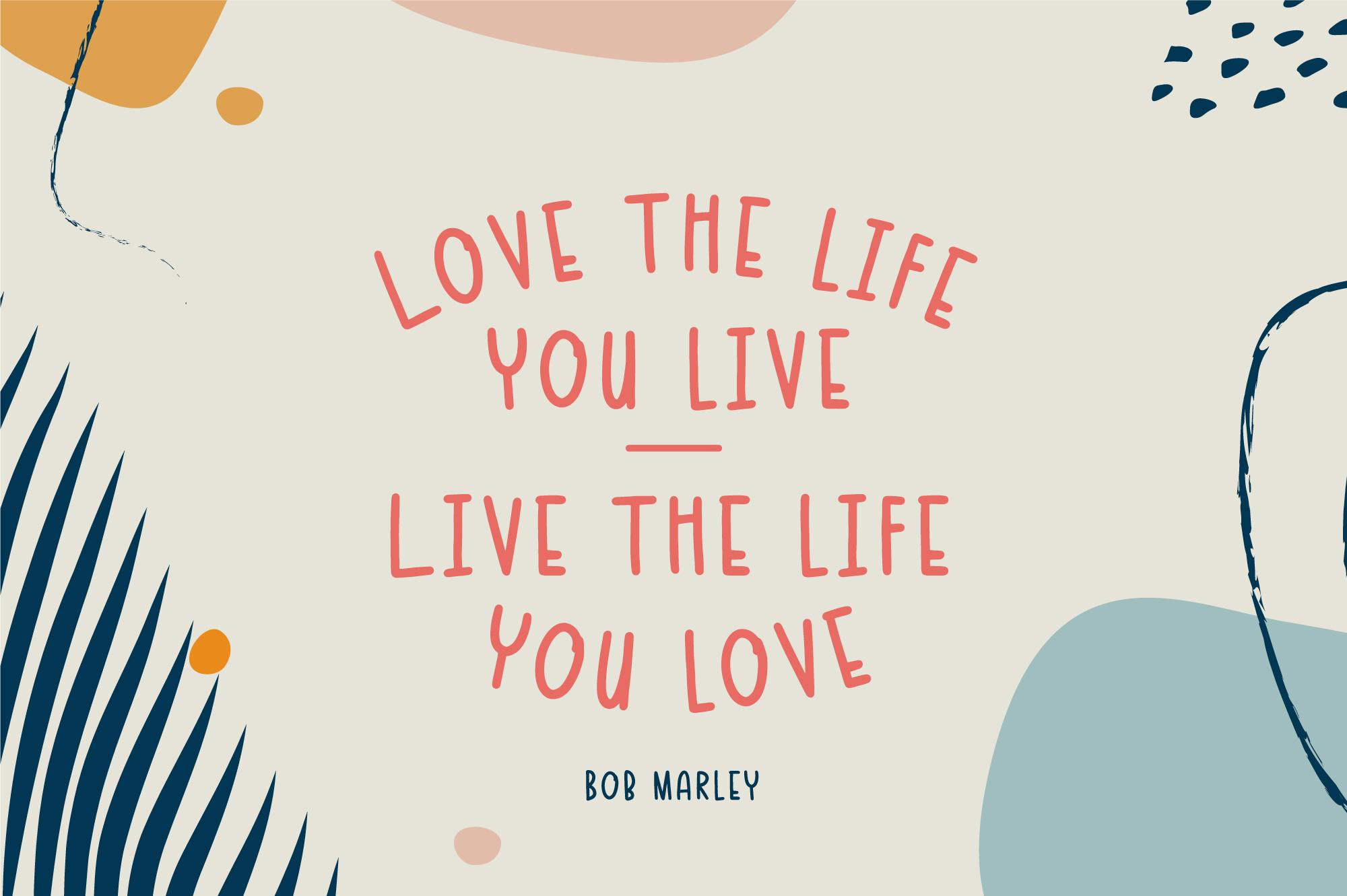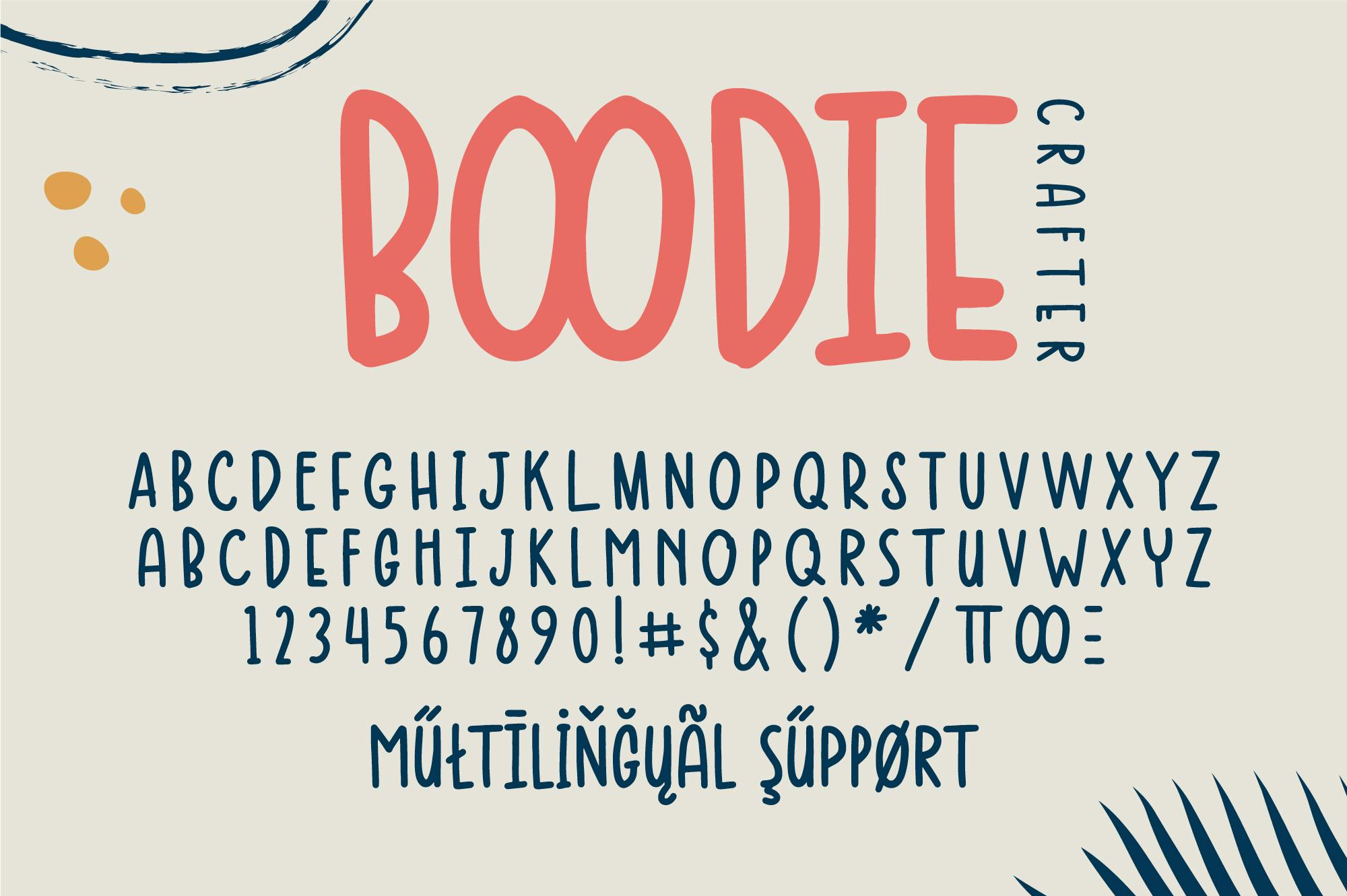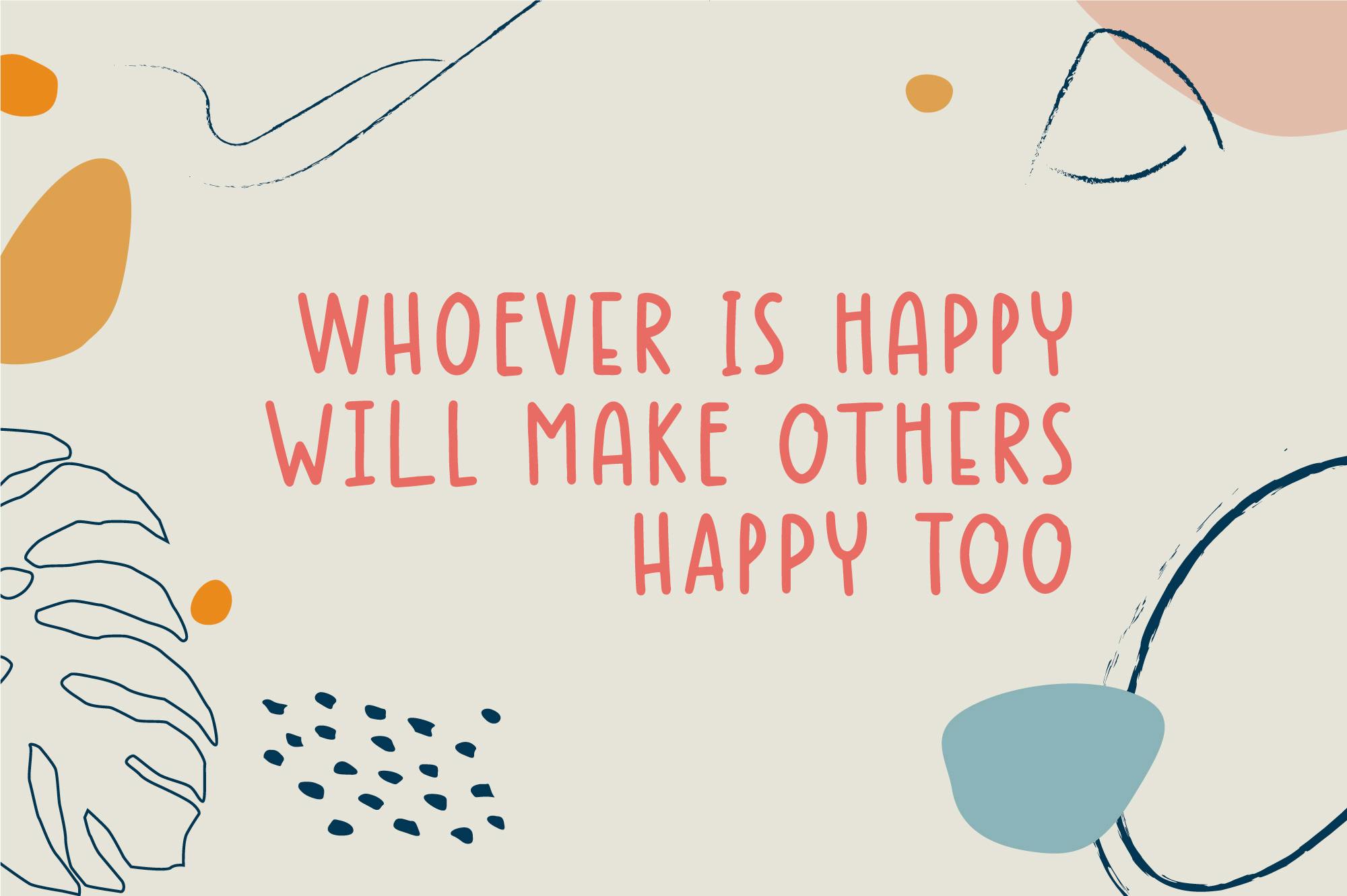
دانلود فونت Boodie Crafter برای طراحی‌های خلاقانه
Boodie Crafter Font
فونت Boodie Crafter با استایلی نوین و وینتج، انتخابی عالی برای پروژه‌های طراحی شماست.
فونت Boodie Crafter یک فونت نمایشی با سبک تازه و وینتج است. این فونت دارای استایلی بازیگوش و مرتب است که برای انواع ایده‌های طراحی مناسب می‌باشد. چه در حال استفاده از آن برای کاردستی، طراحی دیجیتال، ارائه‌ها یا ساخت کارت‌های تبریک باشید، این فونت انتخابی عالی برای شما خواهد بود!
• استایل بازیگوش و مرتب
• مناسب برای طراحی‌های مختلف
• قابل استفاده در پروژه‌های خلاقانه